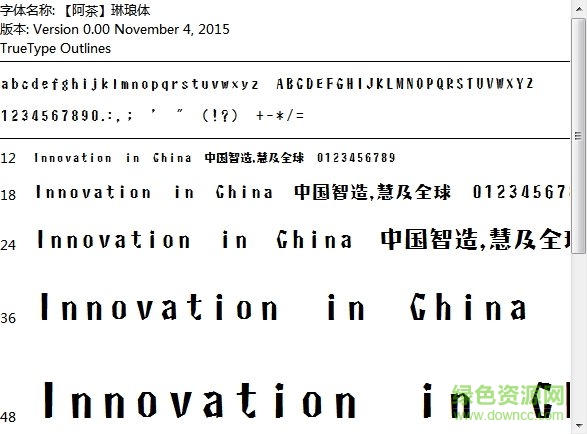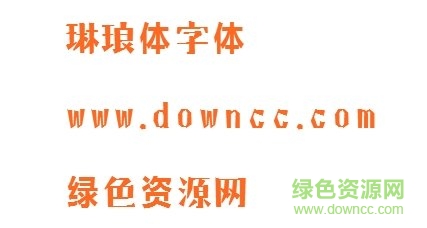
琳瑯體是阿茶制作的一款造型奇特的pop字體,讓字母和漢字均呈現(xiàn)出一種幾何圖案拼接的構(gòu)造,有著很特別的藝術(shù)欣賞體驗(yàn),綠色資源網(wǎng)今日為您推薦!
琳瑯體+黑白emoji是一款由黑體變形的藝術(shù)字體,字體非常個(gè)性,整體效果十分出色。
琳瑯體經(jīng)過阿茶美化修飾后的好看字體,不僅支持繁簡(jiǎn)體、中英文輸入,還自帶emoji表情,十分生動(dòng)可愛,讓你的包裝設(shè)計(jì)、藝術(shù)設(shè)計(jì)更有特色呈現(xiàn)!